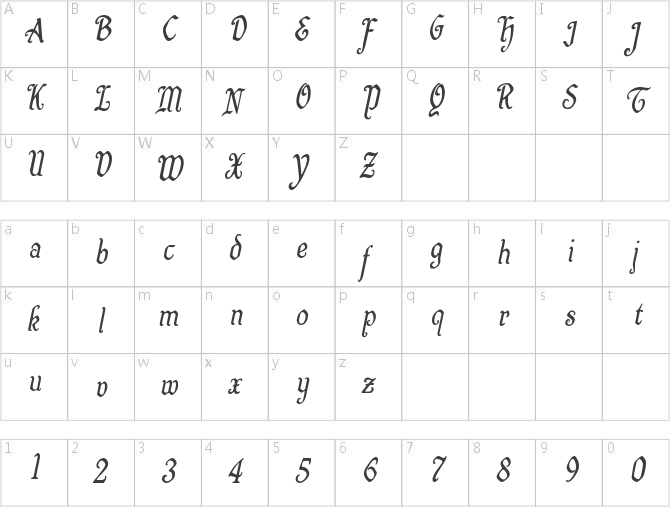
Quill Sword Condensed Italic
Quill Sword Condensed Italic介绍
Quill Sword Condensed Italic字体字库是一款让人赏心悦目、百看不厌的英文字体,适合各类广告和产品包装设计应用,字体大小0.09MB,格式为ttf字体,上传用户是小北,作者/版权方为未知